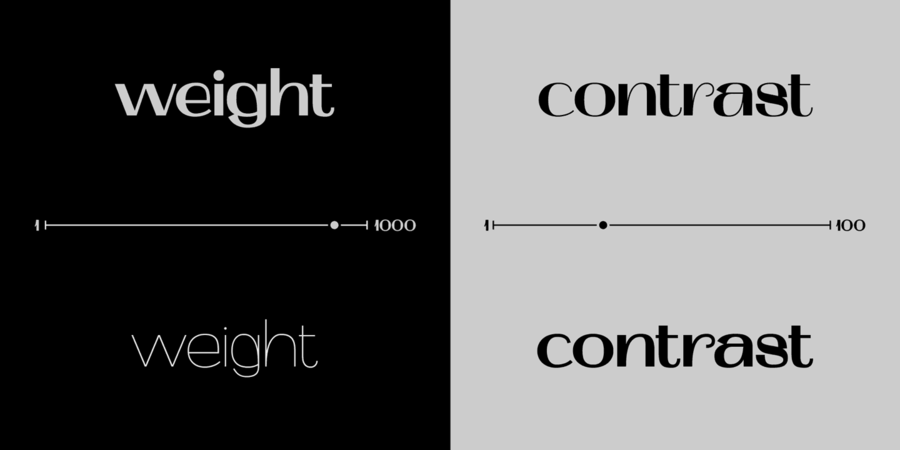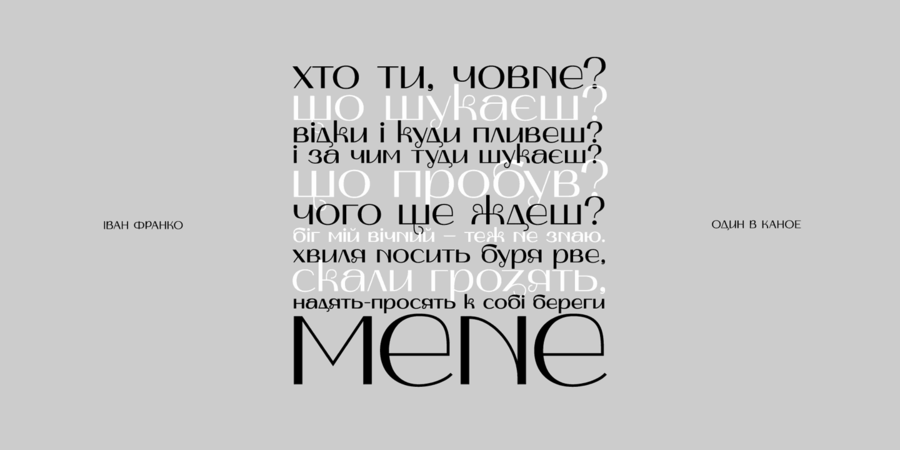
Опис шрифта Mak VariableВаріативна версія популярного українського шрифту Mak. Це акцидентний шрифт з українським характером, натхненний сучасною українською музикою.
Це велике оновлення перших двох безкоштовних накреслень Mak (SemiBold High і Black High), які були створені у 2019 році та набули широкого поширення серед безкоштовних декоративних шрифтів. Велике оновлення полягало не лише в додаванні більшої кількості накреслень, але й у вдосконаленні окремих літер і додаванні нових. Тепер Mak підтримує всі мови на основі латиниці та європейську кирилицю.
Експеременти з історичними формами, контрастність, сміливі конструкції створюють новий образ української кирилиці та латиниці на основі неї.
Шрифт розробив Валентин Ткаченко у 2019-2022 році.
Асоціації з сімейством шрифтів Mak VariableОсобистість і характер гарнітури:
артистичний, добрий, ритмічний, неформальний, грайливий, радісний, цікавий, оригінальний, задерикуватий, характерний, привітний, живий, прикольний, доброзичливий, добродушний, вигадливий, смішний, самобутній, неординарний, мажорний, легковажний, динамічний, дивний, щасливий, творчий, симпатичний, екзотичний, молодіжний, дотепний, потішний, експериментальний, вінтажний, нонконформістський, гнучкий, модний, ефектний, вишуканий, якісний, ламповий, яскравий, літній, вигнутий